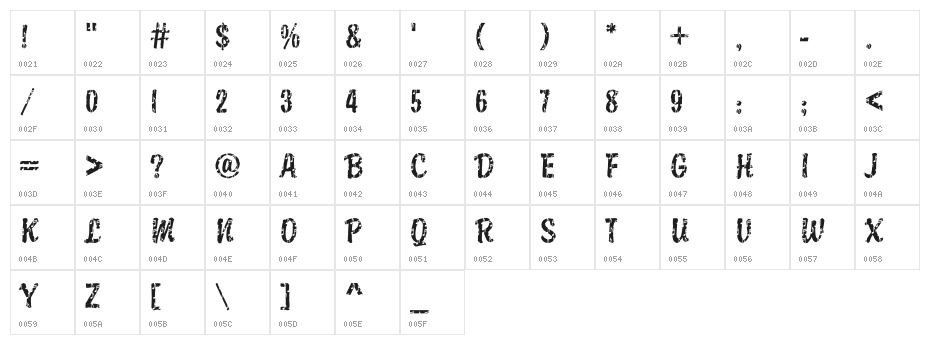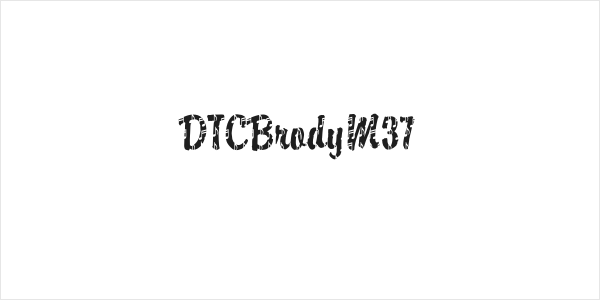
DTCBrodyM37 Font
✎ Script
| النمط العام | Vintage, Edgy |
| مشاريع مقترحة | Ideal for posters, album covers, branding for outdoor or adventure-themed products, and any design needing a vintage, edgy look. |